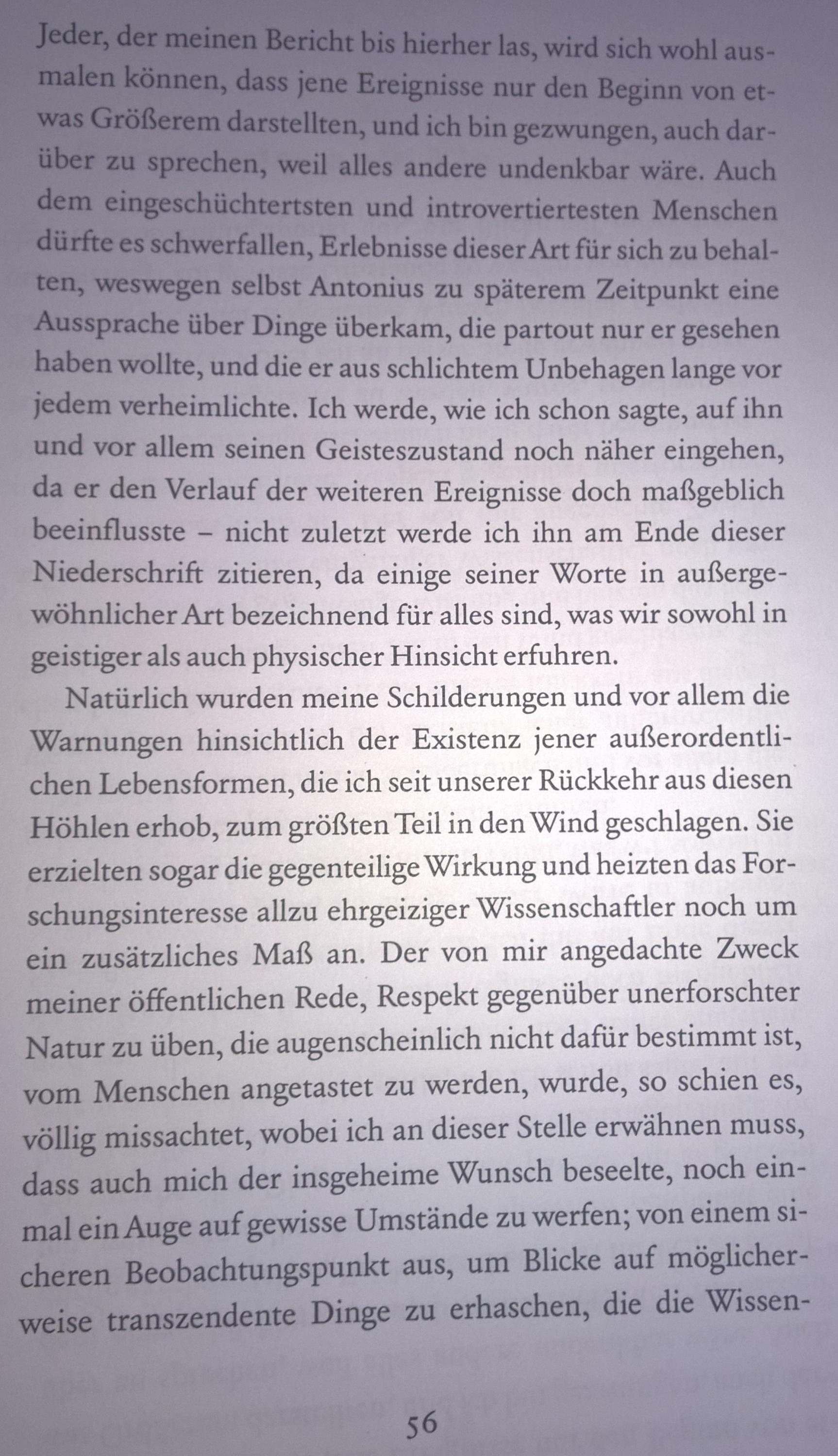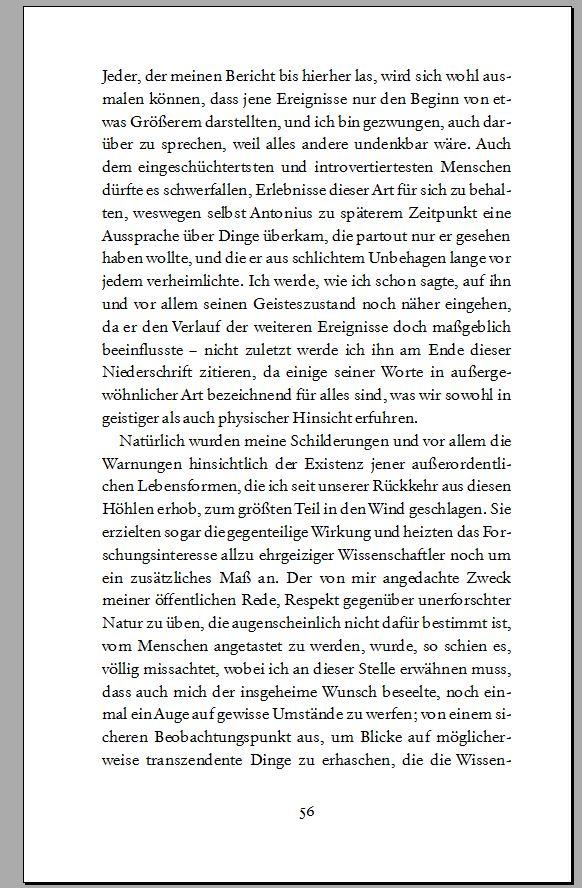
Optimaler Zeilenabstand MVB Verdrigis
Hat schon mal jemand mit der MVB Verdrigis gesetzt? Ich verwende sie grade in Größe 10,5 pt und bei Textbreite 9,5 cm. Allerdings kann ich mich überhaupt nicht entscheiden, was den Zeilenabstand betrifft. Ich zeige euch mal ein Foto bzw. PDF. Aktuell schwanke ich zwischen einem (festen) Abstand von 5,3 - 5,5 mm, wobei ich eher zu 5,3 tendiere. PDF und Foto sind in 5,3 mm. Würdet ihr einen anderen Abstand wählen? Ich neige eher dazu: Lieber zu eng als zu weit :)
Beim PDF denke ich, das ist ok, wobei ich einfach mal ausprobieren würde, ob es vielleicht noch eine Winzigkeit mehr Durchschuss sein sollte. Beim Foto stellt sich bei mir aber merkwürdigerweise nicht das Bedürfnis zum Ausprobieren ein.
Der Zeilenabstand passt für den Schriftgrad dieser Schrift. Entspricht  ca. 10,5/15 pt.
Zur genauen Einschätzung wäre aber auch der wirkliche Satzspiegel von Vorteil. Nehme an, dass dies hier nicht der Fall ist.
Schriftgrad, Schriftart, Satzspiegel etc. sollten besser immer zusammen abgestimmt werden. Nicht isoliert voneinander.
Der Satzspiegel spielt für die Beurteilung des Durchschusses keine Rolle, denn es geht um die Zeilenbildung. Dafür werden abgestimmt: Schriftschnitt und -grad, Laufweite und Wortzwischenräume, Satzbreite und, wird oft vernachlässigt, das Druckverfahren. Ob die Kolumne weiter oben oder unten, innen oder außen steht, ist dafür gleichgültig.
Bei Wortzwischenräumen gilt die Regel: im Zweifel enger, denn Löcher erschweren das Lesen viel stärker als gelegentlich eine Zeile mit sehr engem Wortzwischenraum. Beim Durchschuß kommt es nur auf die Zeilenbildung an, deshalb: im Zweifel weiter. Spürbare Änderungen ergeben sich ab 0,5p/0,2 mm Differenz.
Ich drucke das PDF nicht aus, weil ich dann alles nach einem Ausdruck vom Tintenstrahldrucker beurteilen würde, und der macht die Schrift fetter und die Weißräume demzufolge kleiner. Aber ich würde anregen, den Durchschuß mit der Antwort auf die Frage zu beurteilen: Bilden sich die Zeilen deutlich ab? Das zu beurteilen, kann man den Text: erstens schnell lesen und sich fragen, ob der Blick dabei sicher in der Zeile bleibt oder
gewissermaßen wackelt; zweitens blinzeln und prüfen, ob sich im verschwommenen Bild Zeilen ergeben.
Mein Verdacht nach Bildschirmansichten des PDF in verschiedenen Größen: Durchschuß und Ausschluß (Wortzwischenräume) sind gut, Laufweite müßte erhöht werden.
f und l kommen sich so nahe – die bekommst du mit einer vertretbaren Erhöhung der Laufweite kaum auseinander. Leider hat auch die Vertdigris Pro kein alternatives, kürzeres f.
Dir ein kürzeres f zu machen, solltest du mit FontForge o. ä. hinbekommen. Du kannst aber Mark van Bronkhorst auch anschreiben und ihn darauf aufmerksam machen, dass im Deutschen nicht jedes fl-Paar durch die fl-Ligatur ersetzt werden darf. Wenn sich f und l berühren, ist das eine Ligatur, ganz egal, ob die Zeichen im Font getrennt sind. So sehe ich das zumindest. Und ich kann mir gut vorstellen, dass MVB dir ein kürzeres f kostenlos nachliefert. Der Abstand  müsste sonst um 50 Einheiten erhöht werden, wenn man sich an dem Abstand zwischen dem i-Punkt und dem f orientiert. Und das reißt dann eine zu große Lücke in Wörter, die das Paar enthalten. Dass das f nicht mit den Umlauten kollidiert, liegt daran, dass die Punkte bei denen niedriger gesetzt sind. Funktioniert in dem Fall auch.
Edit: Für das Paar ſl gilt dasselbe. Allerdings enthält der Font kein ſ.
Und dann sollte man auch gleich nach einem Versal-Eszett fragen!
Das sehe ich aber etwas anders. Demnach würde es bei dir auch keine Rolle spielen, wenn ein sehr knapper Satzspiegel, also mit wenig Rand, einen stark durchschossenen Satz aufweist und ein sehr großzügiger Satzspiegel, also mit viel Rand, mit wenig Durchschuss auskäme.
Es geht nicht nur um die Zeilenbildung, sondern um die gesamte Gestaltung der Seite. Aber auch das ist zu kurz gegriffen, es geht um die Gestaltung des kompletten Buches.
Speziell das Zusammenwirken von Zeilendurchschuss und Satzspiegel spielt eben da eine wichtige Rolle.
Aber generell gilt in der Typografie und im Design die Zusammenwirkung aller gestalterischen Elemente in der Gesamtbetrachtung und nicht isoliert voneinander.